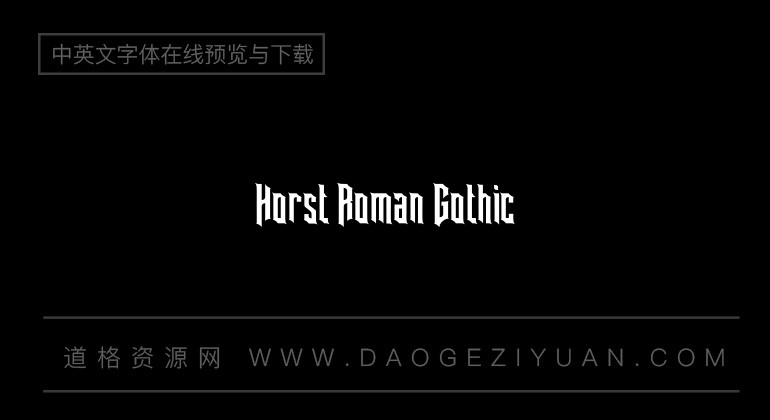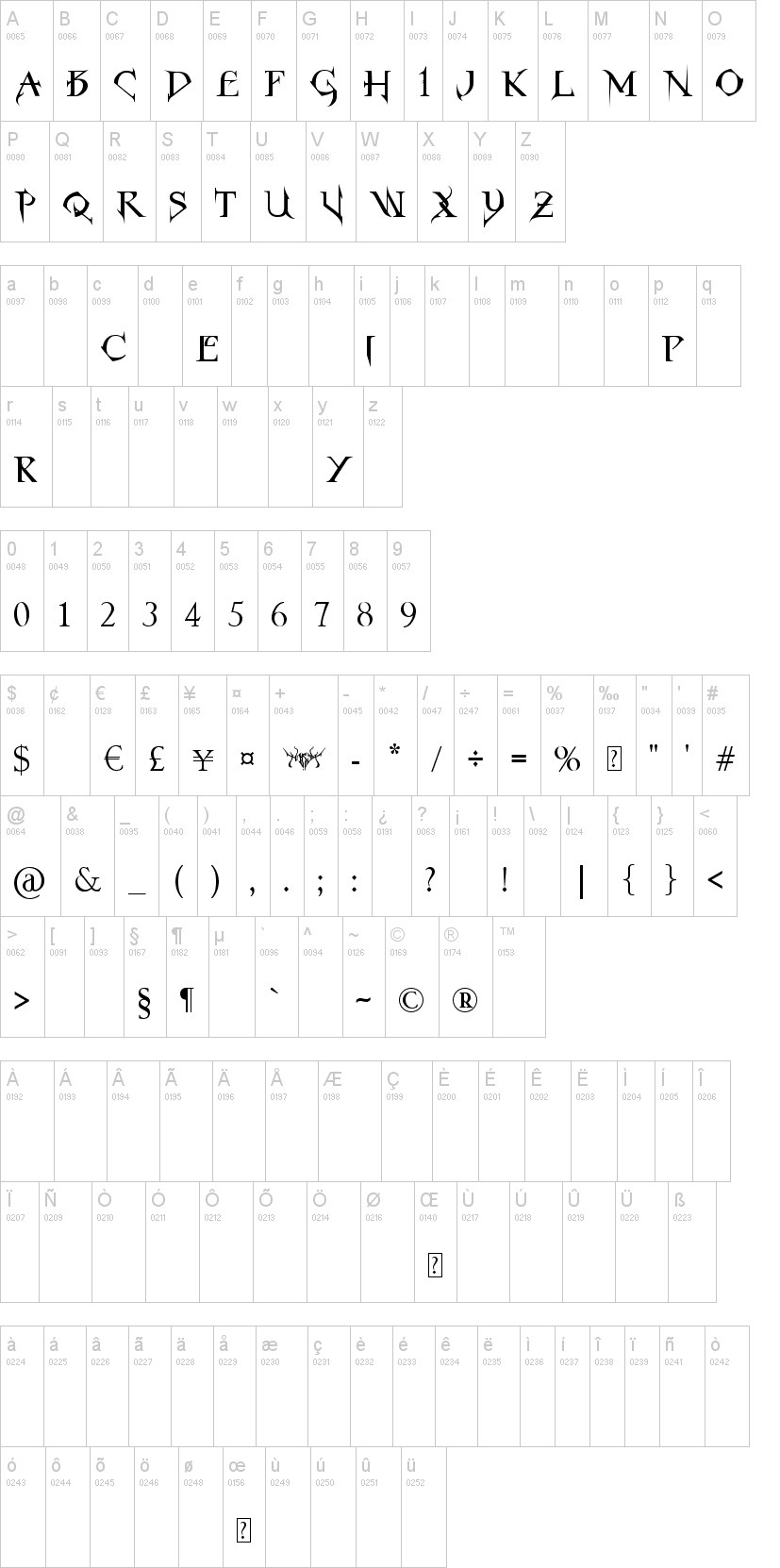
Horst Roman Gothic 字体是由德国设计师Horst Scholz于 1998 年创造的一种黑体字体。它是一种古典风格的字体,结合了罗马字母和哥特字母的特点。它的设计初衷是为了在印刷和发布行业中提供一种独特的字体,以突出文本和标题。这种字体具有粗壮、直线和尖锐的特点,同时也保留了一些罗马字母的柔和和优雅。Horst Roman Gothic 字体适用于各种印刷品、标志和设计作品中,可用于突出标题、品牌名称或其他文本元素。内容介绍
Horst Roman Gothic是一款非常不错的手写艺术字体,具有很好的视觉感,适合于文化类的宣传设计、商业类品牌的广告和产品包装设计以及个性化文字排版等较多场景。